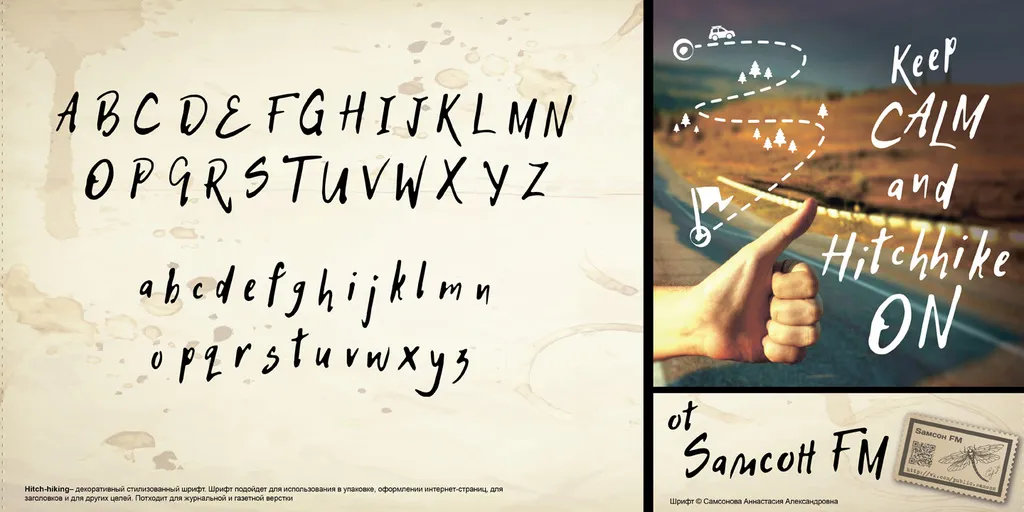
A Hitch Hike Font é uma elegante fonte brush, perfeita para criar designs com estilo atemporal. Criada pelo designer Hamilton, a Hitch Hike é licenciada sob Creative Commons SIL OFL 1.1, garantindo que você possa usar a fonte tanto no uso comercial quanto na versão gratuita. Essa fonte traz um toque de sofisticação e originalidade sem perder o charme moderno. É perfeita para se juntar ao seu projeto de design em uma variedade de ambientes, seja ele impressão, web ou aplicativo mobile. A Hitch Hike não apenas adicionará um toque diferenciado ao seu trabalho, mas também aprimorará sua presença visual com um ar nostálgico e contemporâneo. Estamos certos de que esta fonte irá destacar o seu design em qualquer contexto.